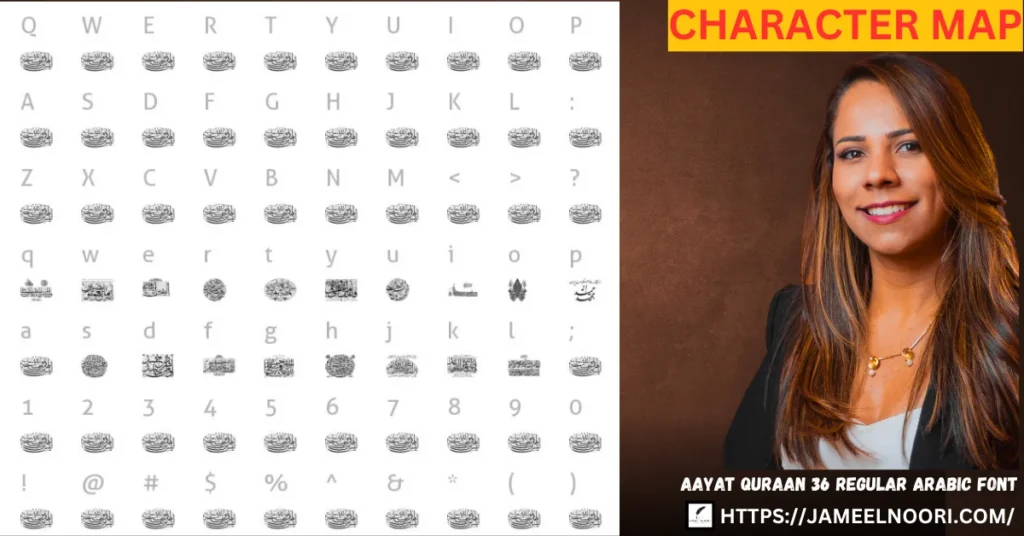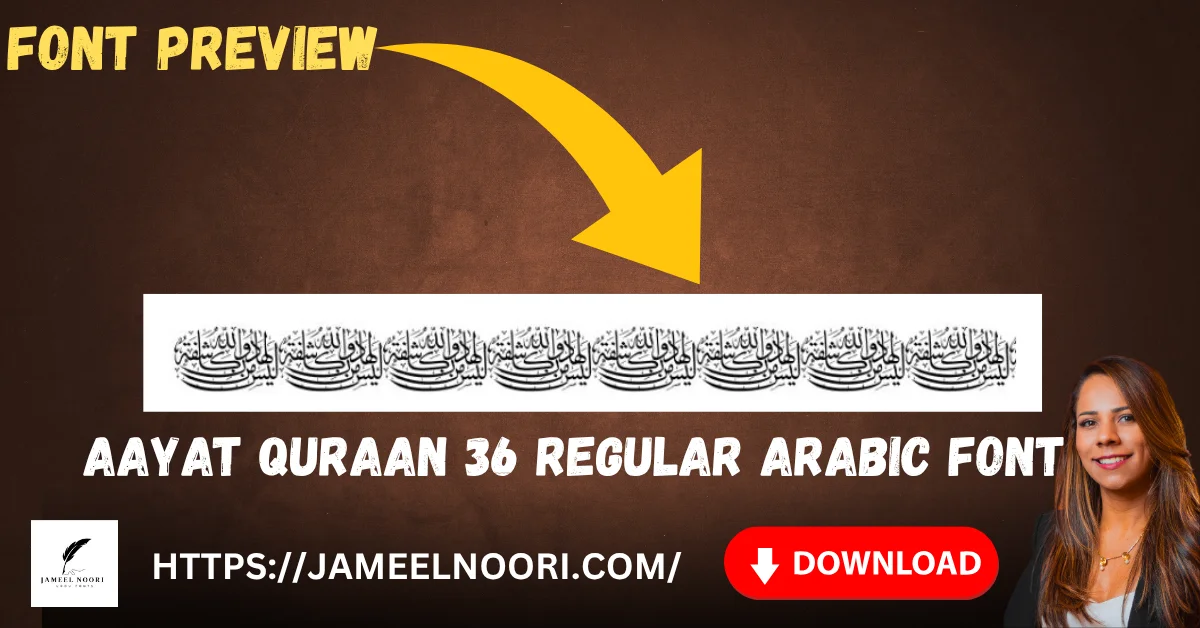
Introduction to Aayat Quraan 36 Regular Arabic Font
Why Choose Aayat Quraan 36 Regular Arabic Font?
- Elegant Calligraphy: Har letter carefully design kiya gaya hai taki Quranic text aur modern Urdu content me easily fit ho.
- High Readability: Small aur large screens dono par clear readability provide karta hai.
Features of Aayat Quraan 36 Regular Arabic Font
| Supported Languages | Urdu, Arabic, and other regional scripts |
| Calligraphy Style | Traditional Arabic calligraphy with modern touch |
Aayat Quraan 36 Regular vs Other Arabic Fonts
Comparison Table
| Font Name | Readability | Popularity | Best Use |
| Aayat Quraan 36 Regular Arabic Font | Excellent | High | Quranic Text, Urdu Books |
| Naskh Font | Good | Medium | Traditional Documents |
| Jameel Noori Nastaleeq | Excellent | Very High | Urdu Articles, Publications |
Benefits of Using Aayat Quraan 36 Regular Arabic Font in Pakistan
- Enhances professional look of Islamic and Urdu content
- Boosts readability for all age groups
- Perfect for digital publishing, print media, and web content
What is Aayat Quraan 36 Regular Font?
It is a TrueType Arabic font designed for Quranic text and Urdu content, offering high readability and elegant calligraphy.
What makes this font different from other Arabic fonts?
Its elegant calligraphy combined with modern readability makes it unique.
Does it support Urdu fonts as well?
Yes, it perfectly supports Urdu fonts and text styling.